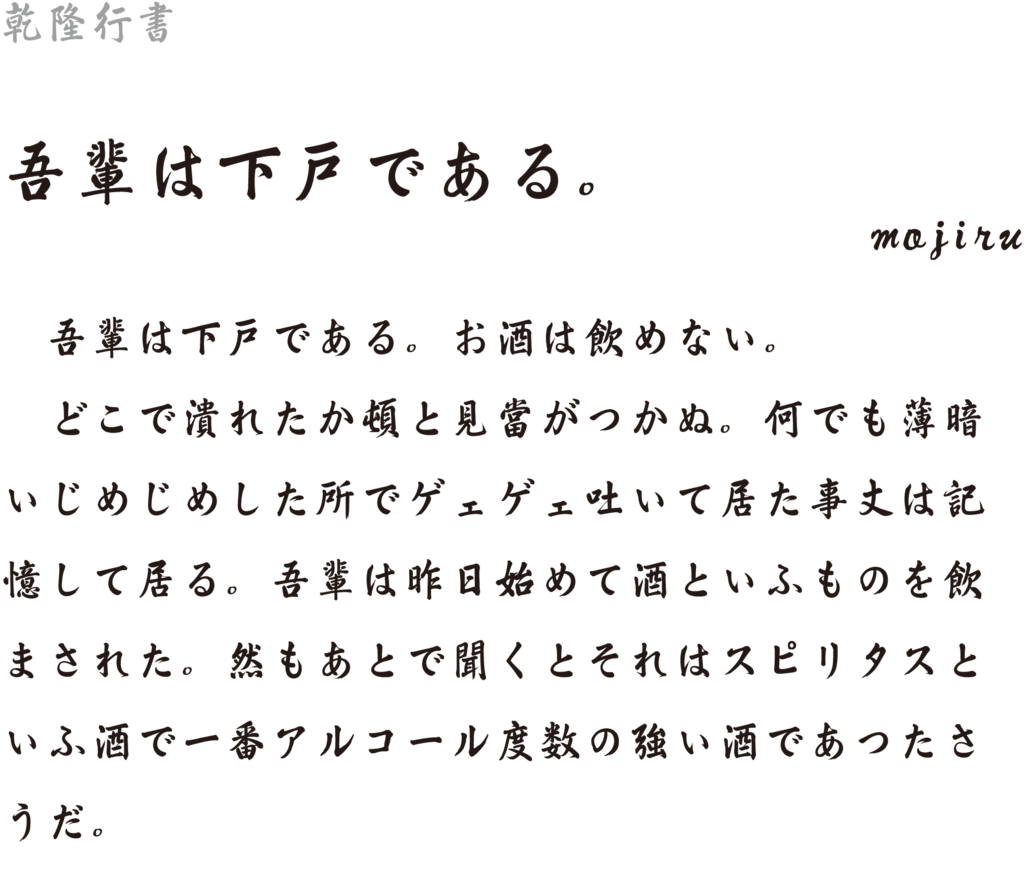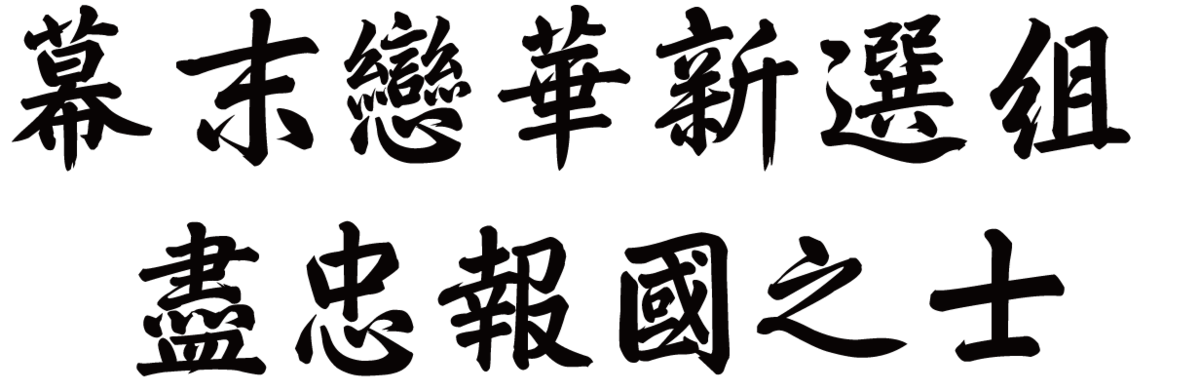
乾隆行書
清朝第六代皇帝の乾隆帝の筆跡をベースに、原本で書かれている毛筆の堂々たる筆運びと連筆を生かしながら、乾隆帝の書風が持つ上品な趣と墨跡を再現した書体。伝統工芸品や食品パッケージ、書籍のタイトルやデザインに筆文字の風合いを持たせたい場合にも適している。
乾隆行書の書体見本
「幕末恋華新選組 尽忠報国の士」の繁体字中国語のテキストに、ダイナフォント乾隆行書の繁体字中国語版フォント「DFQianLongXing W7( 繁体字中国語版)」が採用
株式会社ブリッジ開発、株式会社ディースリー・パブリッシャーが2021年6月17日に発売した、Nintendo SwitchおよびSteam用恋愛アドベンチャーゲーム「幕末恋華新選組 尽忠報国の士」の繁体字中国語のテキストに、ダイナフォント「DFQianLongXing W7(乾隆行書 繁体字中国語版)」が採用されている。
採用理由は、日本の歴史物ということで筆文字を各所のデザインに使用しているが、他言語対応することになり、日本語と中国語両方に対応し、かつ人名や歴史用語に使用される古い漢字に対応できる筆文字フォントが課題となっており、日・英・中で統一した雰囲気のフォントを使用できるという点で採用になったとのこと。